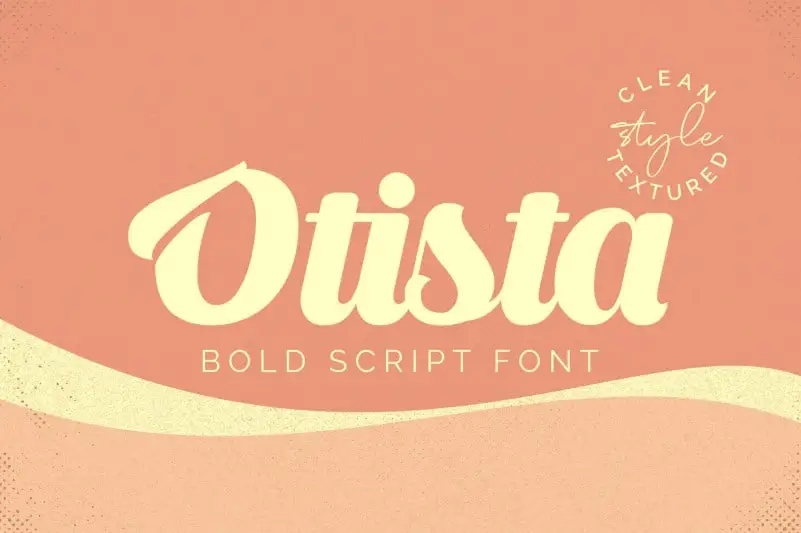
A Otista Bold Script Font, criada por Omotu na plataforma de design 99designs, é uma tipografia script elegante e bold inspirada nos posters retro dos motociclistas. Esta fonte vem com dois estilos: um limpo e outro texturizado. Perfeita para logomarcas, identidades corporativas, embalagens, painéis de propaganda, websites, design de mídia social, edições, cabeçalhos, propagandas e muito mais. Suas linhas arredondadas e seus traços robustos criam um visual que combina elegância com uma atmosfera vintage nostálgica, perfeito para estilos de arte retro ou modernos, dependendo do uso proposto. Engane-se sobre a complexidade da Otista Bold Script: é fácil de ler mas possui o charme desejável de um design retrô.